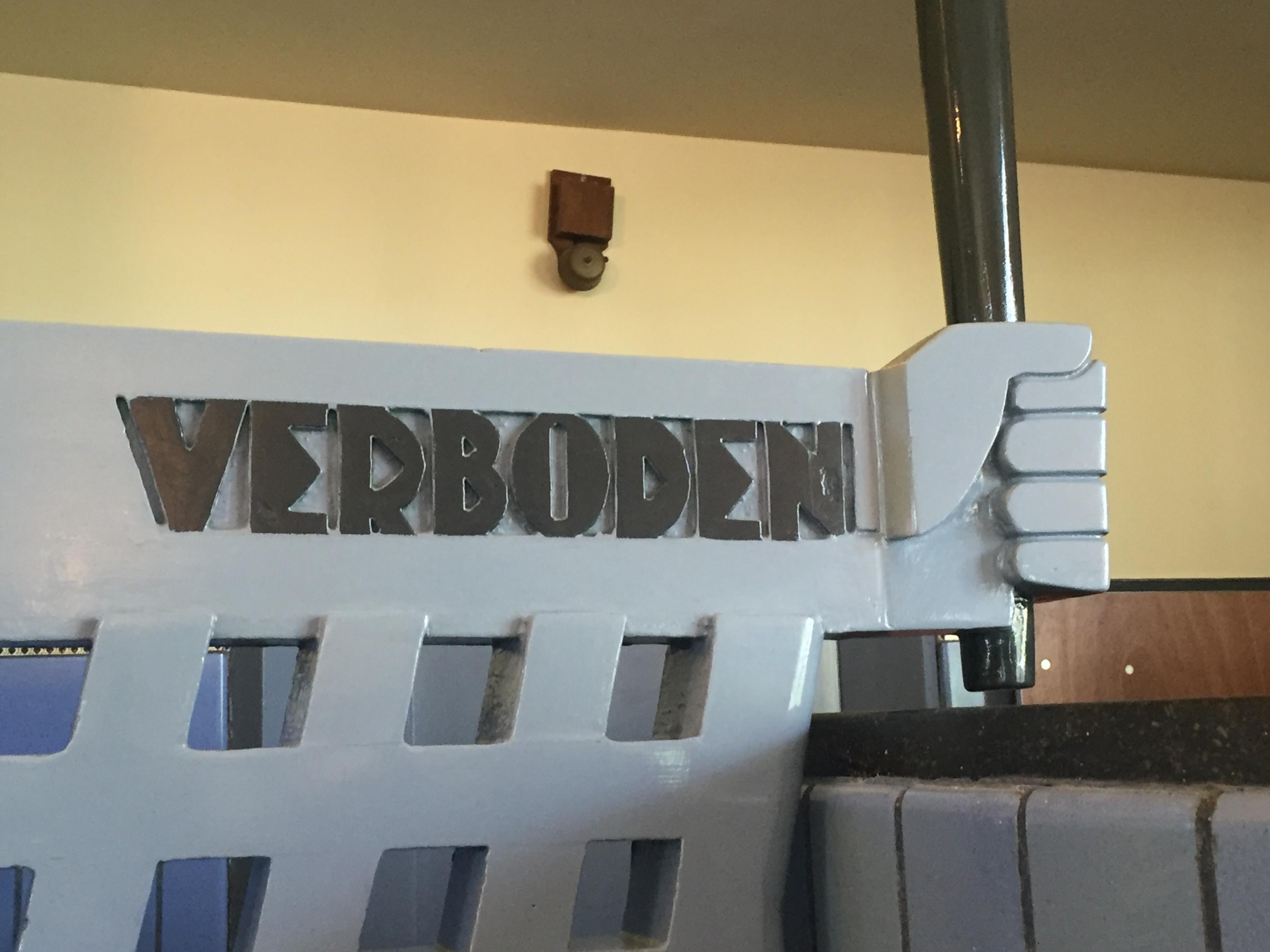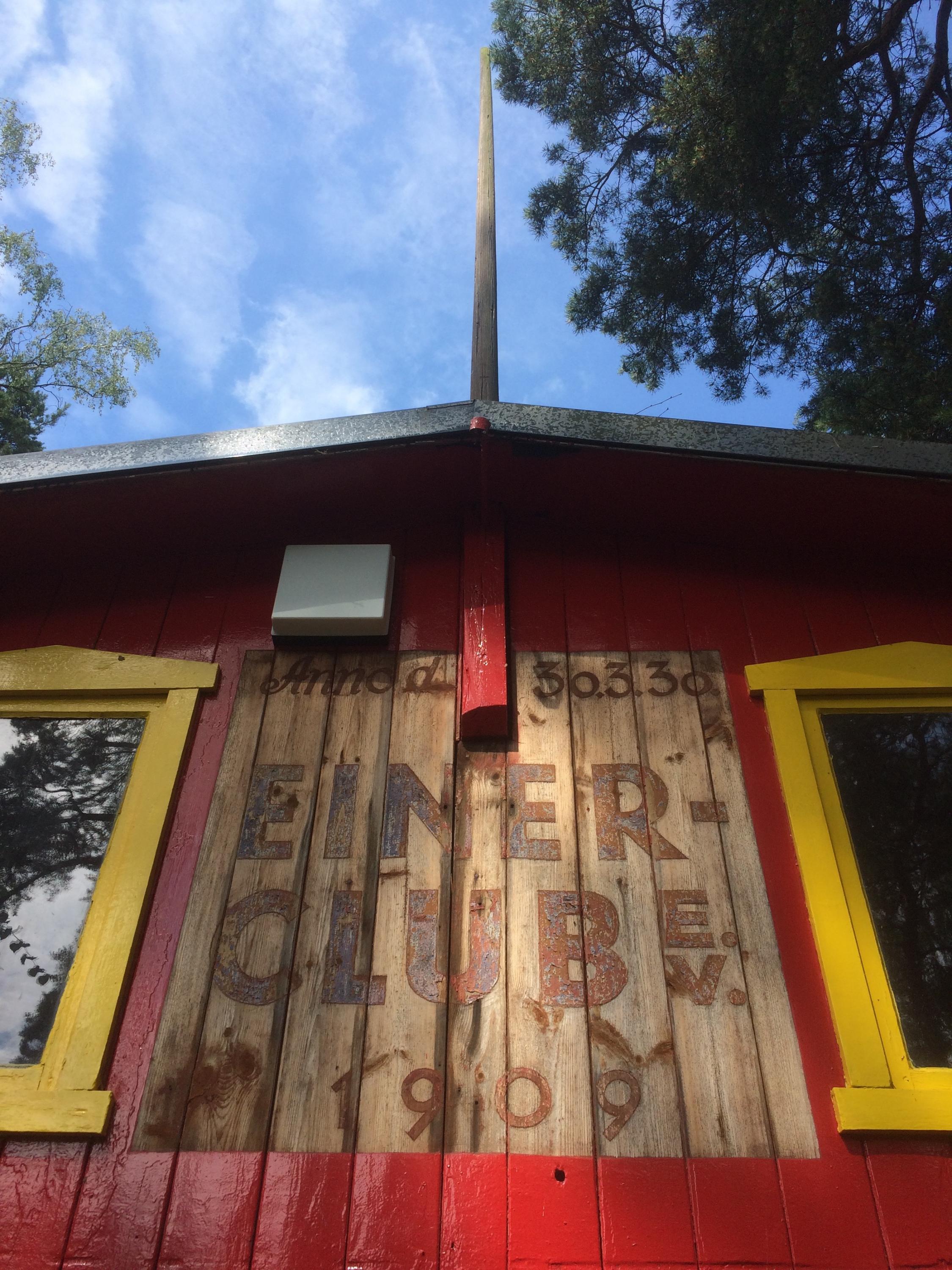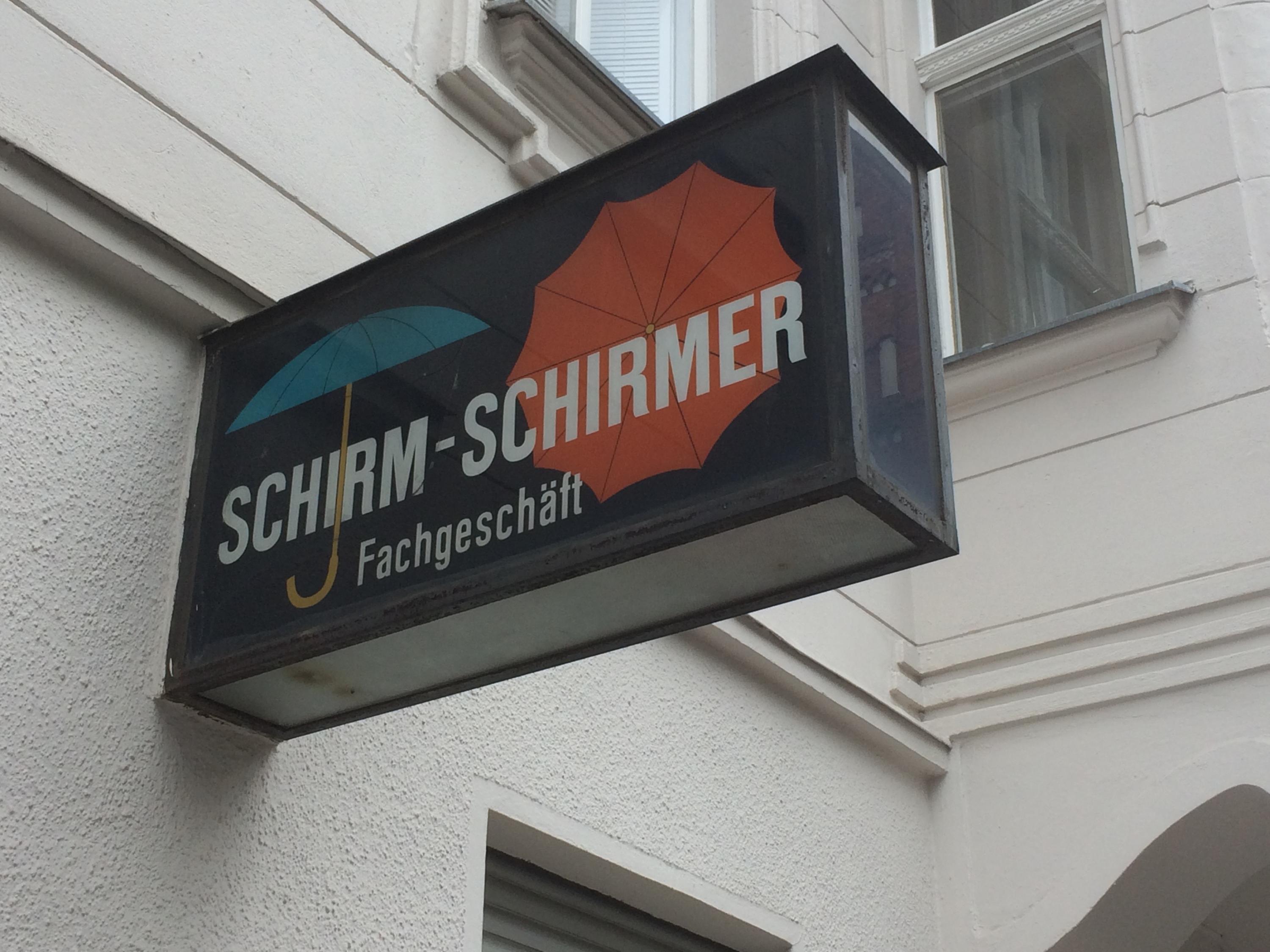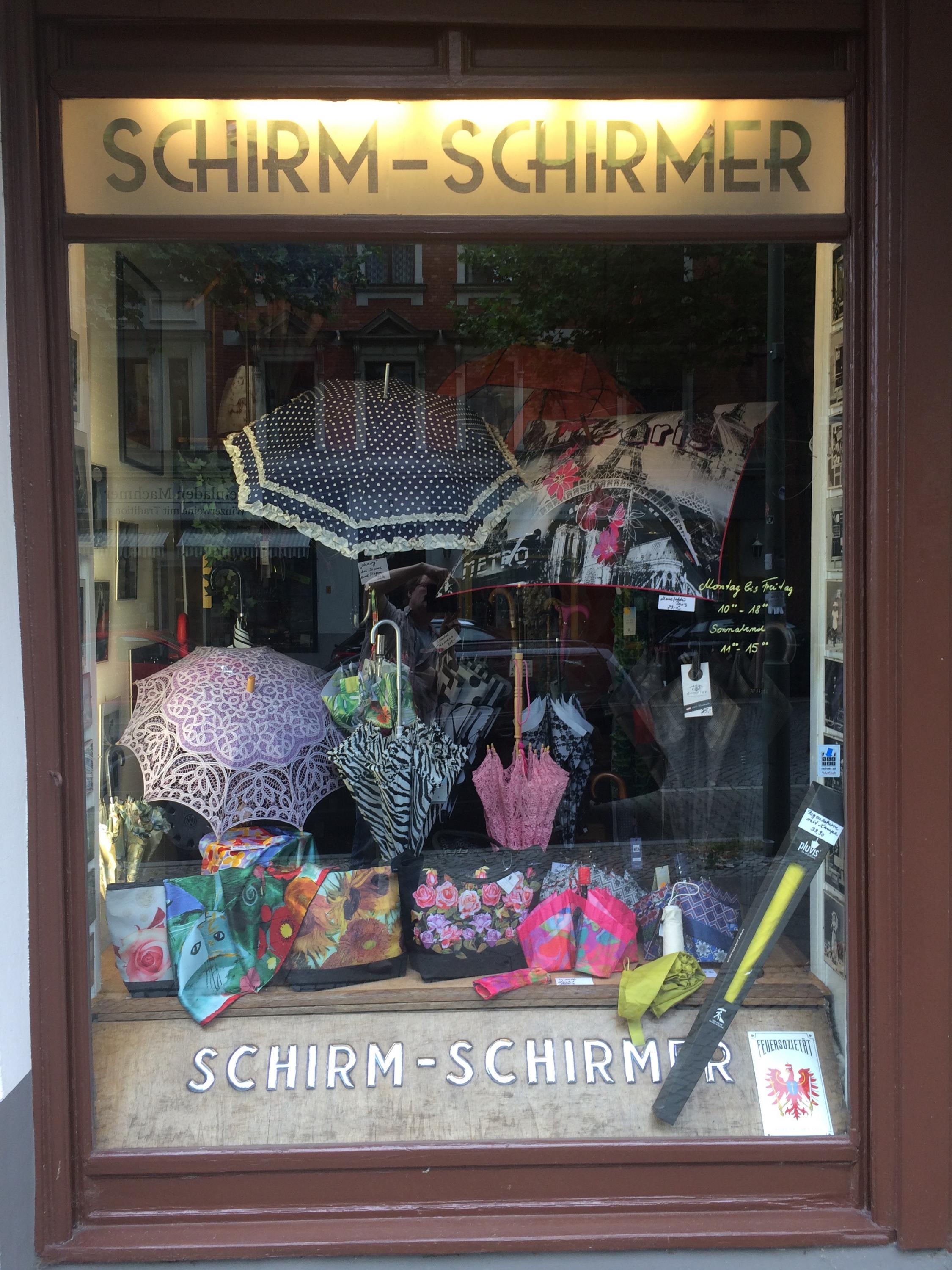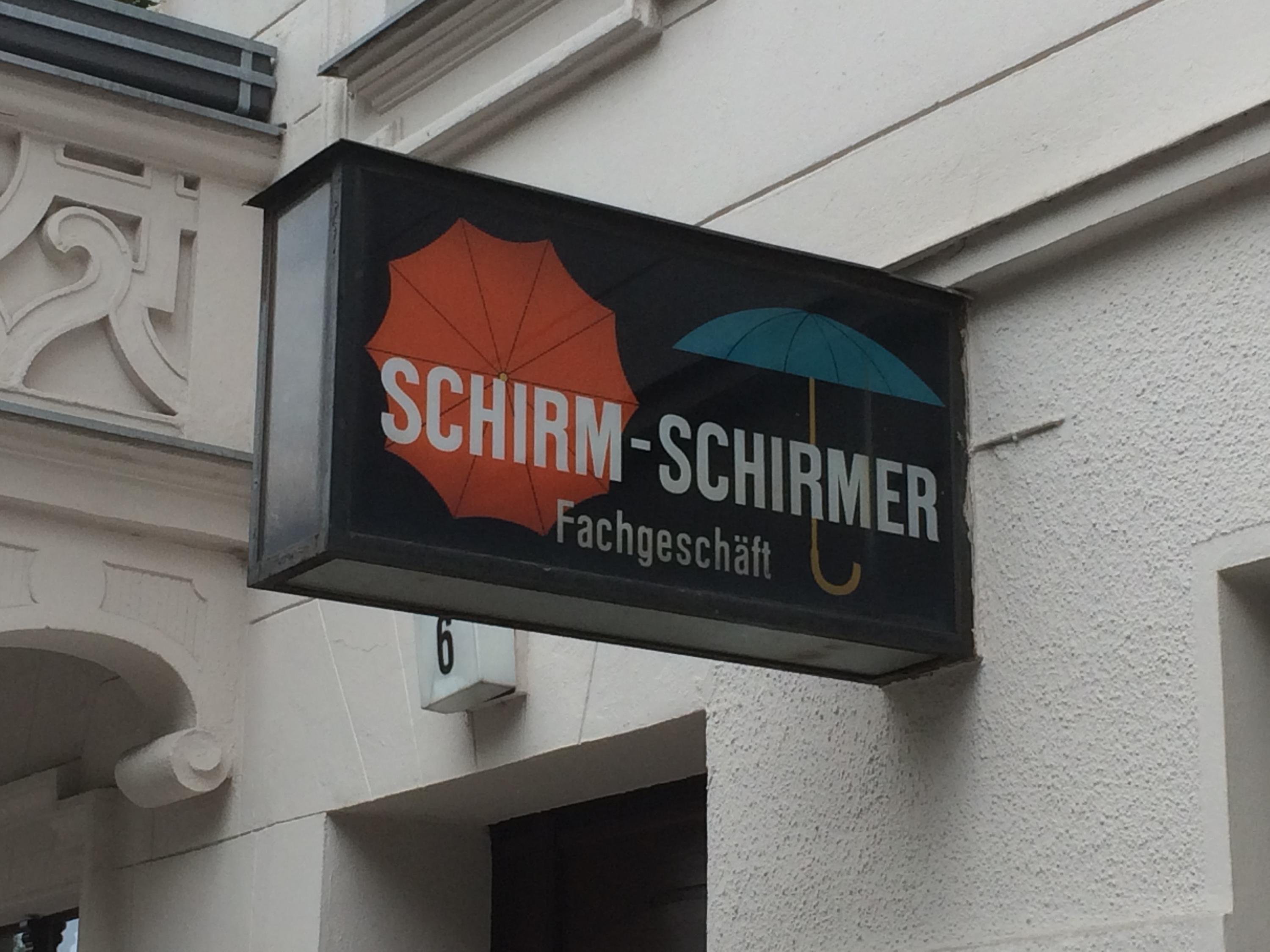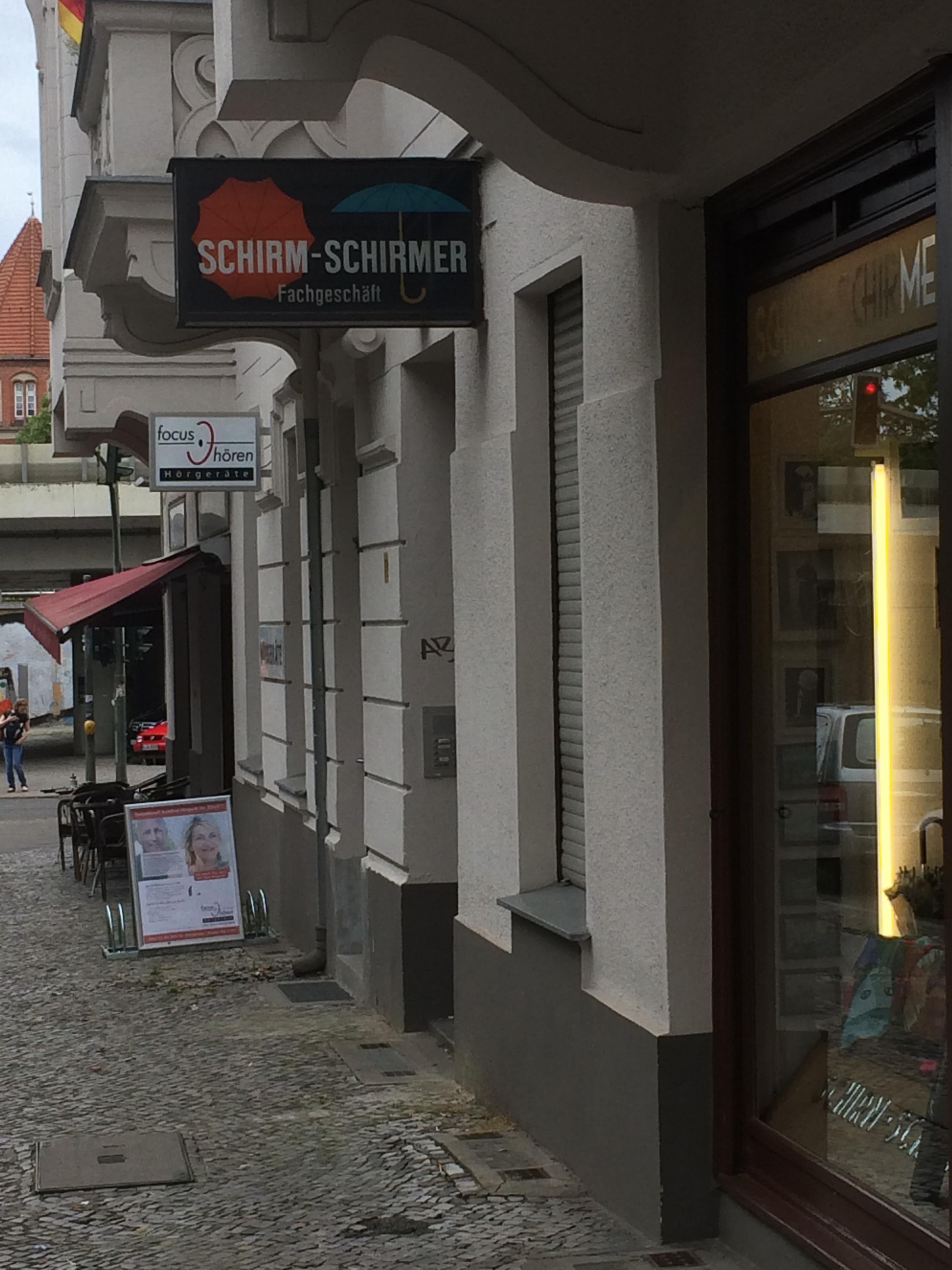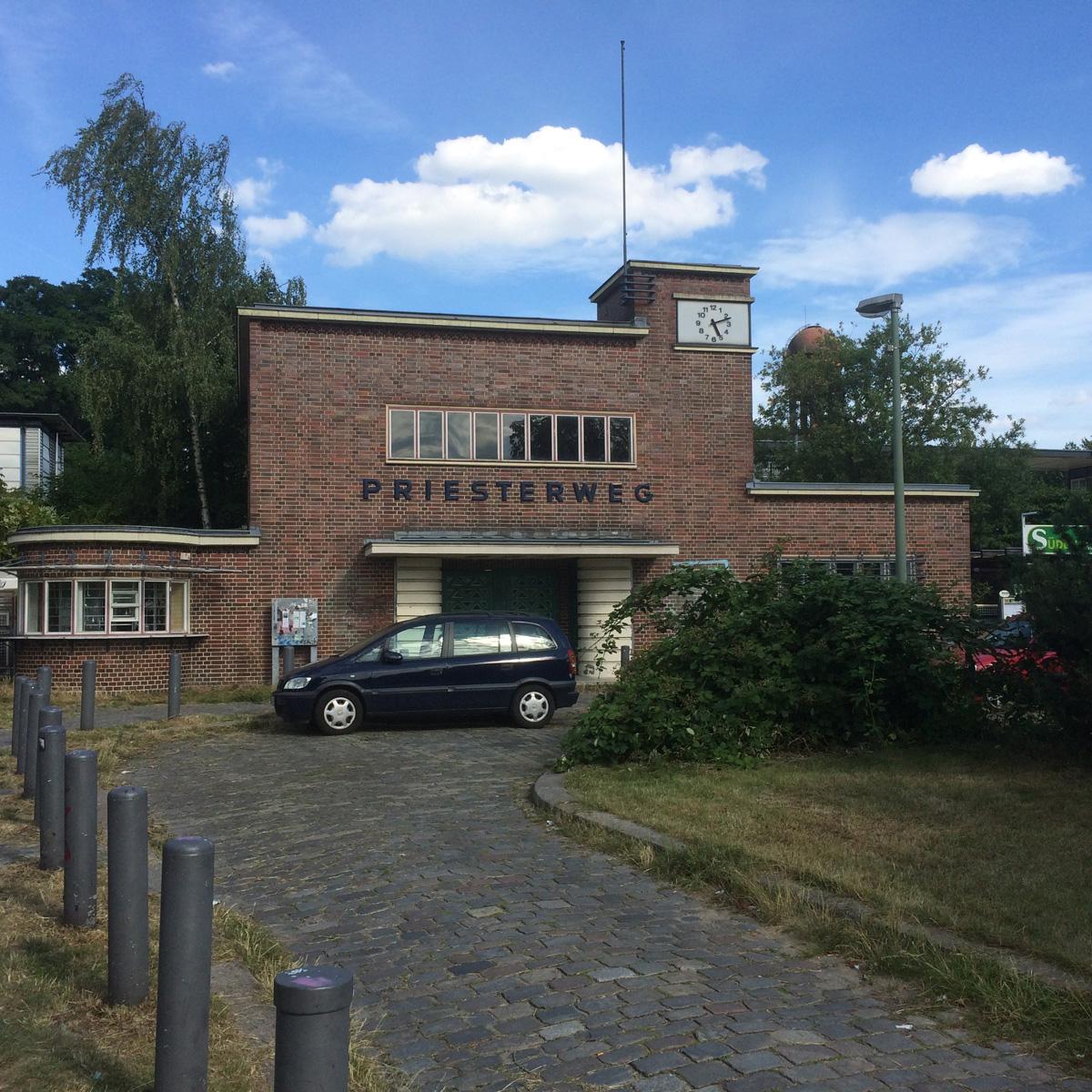
Typostreifzug durch die Stadt ...
Entdeckt im Bergmannkiez, Berlin, Golßener Straße (um die Ecke in der Fidicinstraße ist die Kfz-Anmeldestelle Friedrichshain-Kreuzberg)
Ein paar Impressionen unseres wunderbaren Frankreichurlaubs:
Chartres
als wir abends noch durch die Stadt geschlendert sind, gab es eine unglaubliche Illumination auf den Fassaden der Kathedrale, die mich komplett geflasht hat. Besonders als sich aus dem Muster plötzlich Buchstaben entwickelt haben:  :ilovetype:
Und das absolute Highlight der Reise war eine Architekturführung in „Het Schip“ ,
Bilder aus dem Postamt:
Diese Tür hat den öffentlichen Bereich vom dienstlichen Bereich getrennt. Eine eindeutige Aussage :-DIMG_1095.jpg
Hausnummern
Baujahr (die 2te 19 ist nur von der Seite zu sehen)
und  eine schöne Dose in der Musterwohnung
Und passenderweise gab es im Stedelijk noch eine super Ausstellung zum Wohnen in der „Amsterdamer Schule“.
Architekturführung und Ausstellung kann ich jedem nur empfehlen!
Front eines Bootshauses auf dem Gelände des  Wassersport-Vereins 1921 e.V., Berlin Grünau. Wurde beim Neuanstrich freigelegt und so stehengelassen …
Sehr schön! So gleichmäßig und gut gestaltet war die Vorlage sicher nicht handgemalt. Was meint ihr: wie wurde das wohl gemacht?
Möglicherweise montierte Buchstaben, Metall, Holz, und die Überbleibsel sind Reste der Montage?  Hab dazu leider keine Quelle und war nur kurz zu Besuch vor Ort …
Hier noch was von der gestrigen Shopping-Tour, hat fort bestanden im Windschatten einer der grössten Einkaufsstraßen im Süden Berlins (Schloßstraße), wollte ich schon immer mal fotografieren.
Vor den Toren der grossen Stadt haben sich noch ein paar Relikte enthalten, die in der Stadt schon lange untergegangen sind (wichtige Stätten der Kindheit wie das DEDY-Kino in Berlin-Schmargendorf wurden in einen ALDI umgewandelt) … entdeckt auf dem Weg nach Beelitz.
Da gibt mal wieder ein weiteres Traditionsgeschäft in Frankfurt den Betrieb auf.
Die Leuchtschrift will ich hier mal verewigen, wer weiß, wie lange sie noch hängt …
ö.
Tüt oder Tröt hätte ich auch schön gefunden :-)